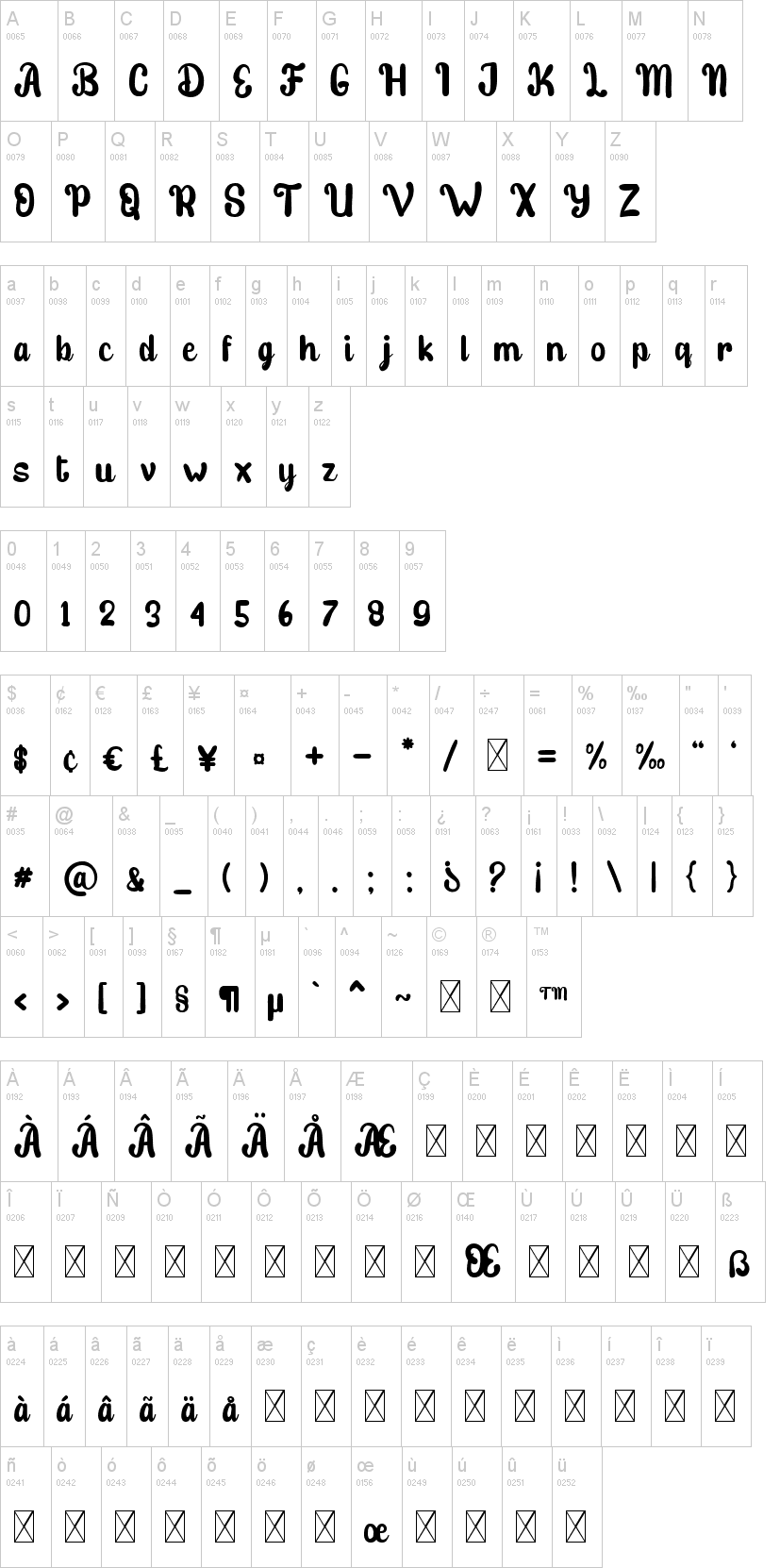
Stibold
? Stibold是一款极具特色的字体,它的特点是有一种极具古典风格的复古设计,字体具有清晰的结构,视觉上有着极强的穿透力。它的字形是由英国设计师Stephen Rappin设计的,让人们有种深刻的印象。它的字体结构清晰,每个字母的笔画都非常精细,极具视觉美感。Stibold 字体适用于各种类型的设计,特别是在印刷品上,它能够给人们一种优雅、大气、古典的感觉。
Stibold是一款非常不错的手写艺术字体,具有很好的视觉感,适合于文化类的宣传设计、商业类品牌的广告和产品包装设计以及个性化文字排版等较多场景。
Stibold字符映射图